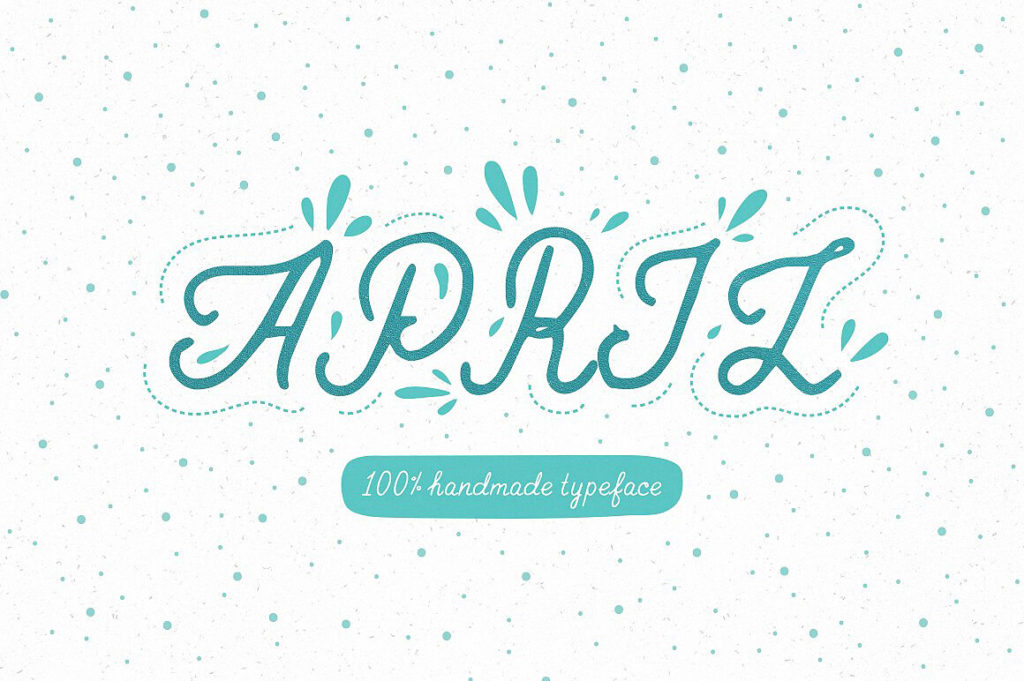
выразительный рукописный шрифт, имитирующий естественное письмо кистью или маркером. Изначально разработан как латинский дисплейный шрифт (авторство часто связывают с Gaelleing), а кириллическая адаптация позволяет использовать его в русскоязычных проектах без потери стиля. Мягкие, плавные линии и лёгкая небрежность начертания создают тёплое, доверительное настроение. Отлично подходит для заголовков, акцентных надписей и декоративной вёрстки. Скачать бесплатно кириллическую версию можно на нашем сайте